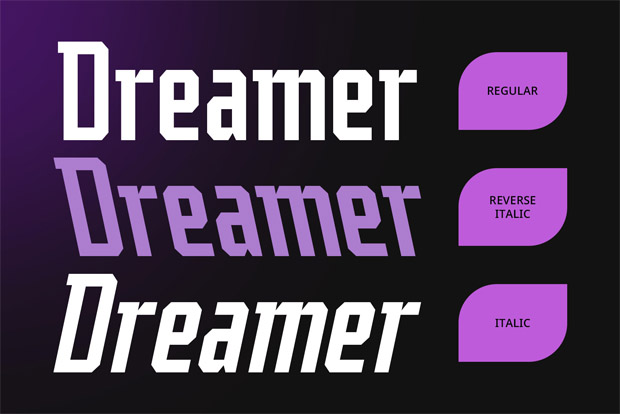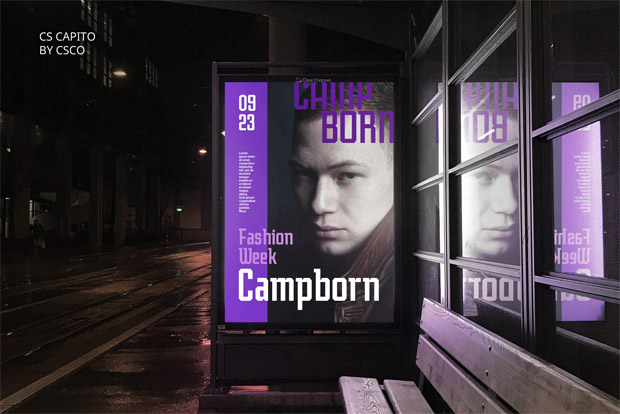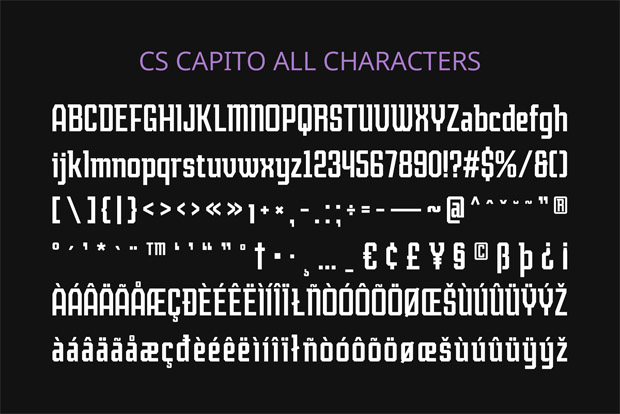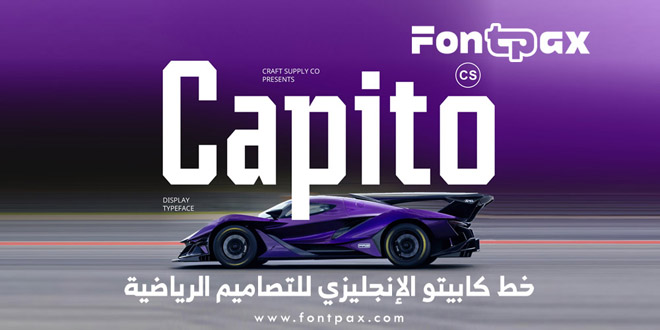
خط كابيتو الإنجليزي للتصاميم الرياضية .. هو خط عرض عصري بدون تذييلات، مصمم بأسلوب رياضي وحيوي. يتميز هذا الخط بأشكاله الحادة والديناميكية، ويجسد إحساسا بالحركة والسرعة، مما يجعله مثاليا للتصاميم التي تهدف إلى التعبير عن الطاقة والنشاط بفضل أشكال حروفه الجريئة، كما برز القوة والحسم، مما يجعله خيارا ممتازا للمشاريع الرياضية.
خط كابيتو الإنجليزي للتصاميم الرياضية